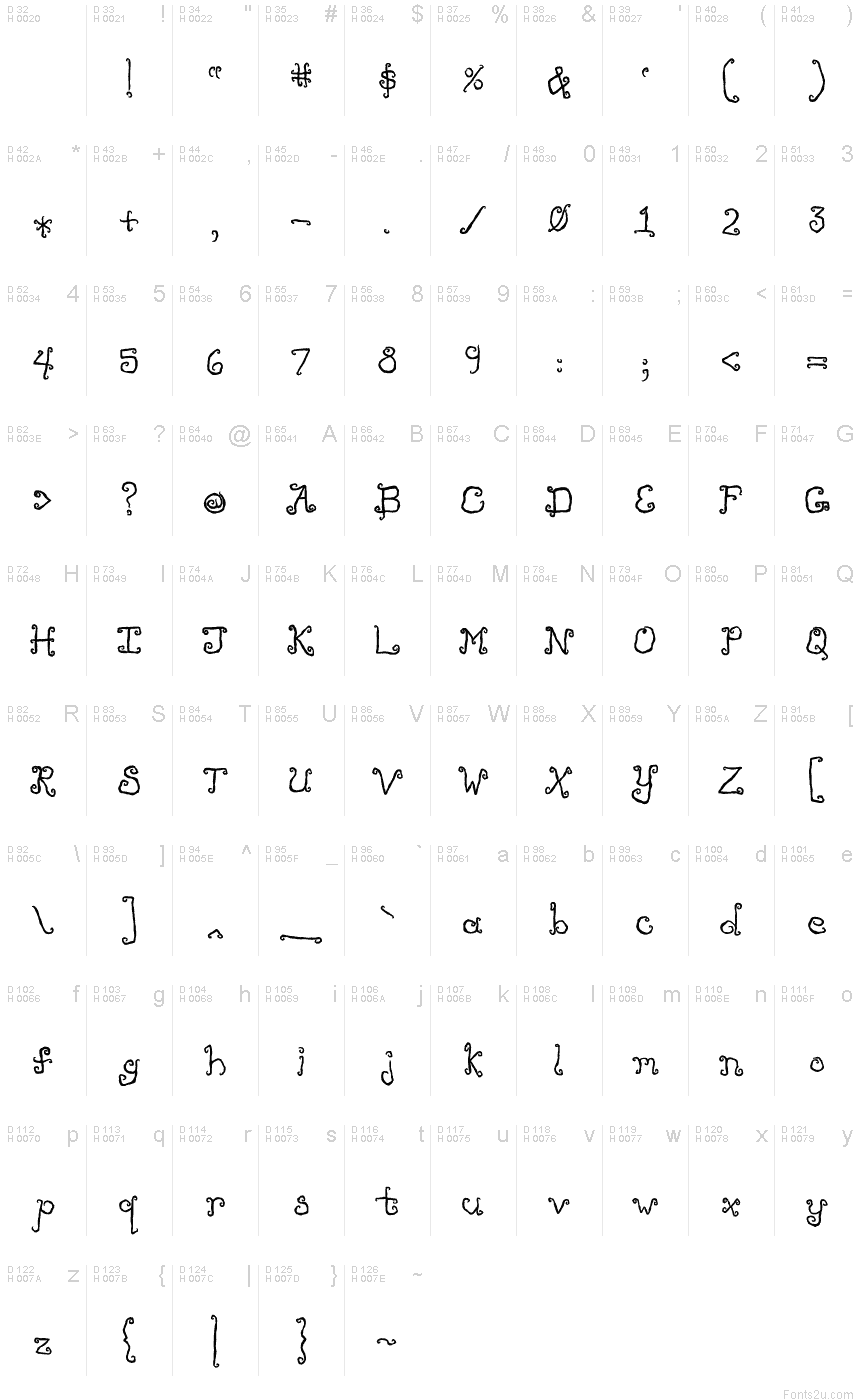
Like Cockatoos Bold
Cockatoos, darmowy, upiorny font typu display autorstwa Kevina Richeya, zamienia cienkie litery w zabawny, nawiedzony gryzmoł. Pociągnięcia sprawiają wrażenie odręcznych i nieco nierównych, a zapętlone haczyki i korkociągowe loki nadają całości lekki, a nie brutalny charakter.
Świetnie pasuje do plakatów, ulotek na Halloween, okładek książek, tytułów gier indie i nieszablonowego brandingu, gdzie litery same opowiadają historię. Jako darmowy font, sprawdza się również w krótkich nagłówkach, logotypach i inicjałach – spiralne końcówki nadają nawet krótkim słowom tajemniczy, bajkowy klimat.